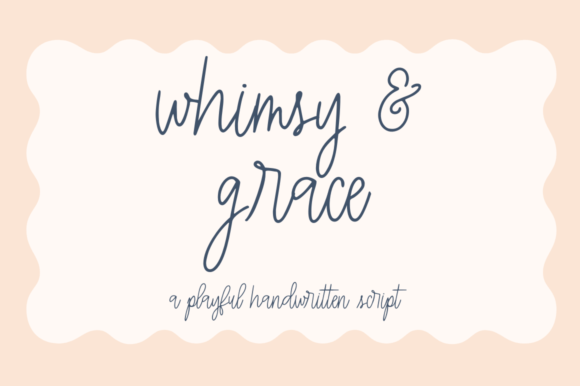
Whimsy & Grace
Пошук відповідних елементів дизайну може бути складним, але Whimsy & Grace пропонує виняткову колекцію, яка миттєво покращить вашу роботу.
Створений з високою точністю, Whimsy & Grace забезпечує чисті вектори, плавну типографіку та комерційну ліцензію для вашого спокою.
Незалежно від того, чи створюєте ви продукти POD (друк на вимогу), весільні запрошення або графіку для соціальних мереж, Whimsy & Grace стане ідеальним вибором.